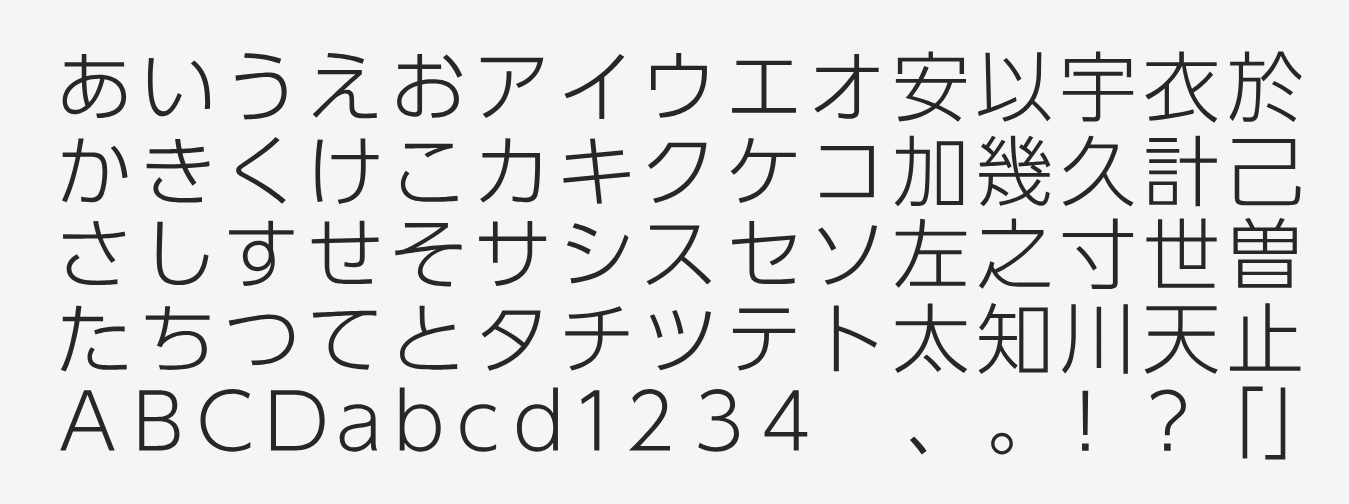
クラウド請求書作成サービスで
UD新ゴを採用
インボイス制度で利用者が広がる
電子帳票をよりアクセシブルに
インボイス制度の導入や電子帳簿保存法の改正に伴って請求書の電子化が進み、請求書発行サービス市場の拡大が続いている。ユーザーの選択肢も増えるなか、中小企業や個人事業主にフィットしたサービスで存在感を示しているのが、ヴェルク株式会社の開発したクラウド請求書作成サービス『board』だ。
同社は業務効率化につながる機能の開発はもちろん、Webアクセシビリティの改善にも積極的に取り組んでいる。より多くの人にとって見やすい帳票とするべく、2023年10月には書類で使用するフォントを変更し、新たにモリサワのユニバーサルデザインフォント(以下、UDフォント)である「UD新ゴ」を導入。同社の代表取締役であり『board』開発者である田向祐介氏に、フォント導入の経緯やアクセシビリティへの取り組みなどを伺った。
中小企業のビジネスモデルに即した『board』の設計
『board』は見積書や請求書の作成をはじめ、営業管理や受発注管理などの周辺業務を一元的に管理できるクラウドサービスで、数人から数十人規模の中小企業や個人事業主を主な対象としている。開発の経緯をたずねると、「僕が欲しかったんです」という答えが返ってきた。
「開発当時(2014年)、請求書を作成するサービスはあっても、業務管理ができる中小企業向けのサービスが無かったのです。業務管理までできるサービス自体は存在しましたが、支払う利用料のケタが違い、中小企業にとっては現実的ではなかった。それならば自分で作ろう、事業にならなかったら社内システムにすればいいや、という感覚でスタートしました」
『board』の開発には、実際に経営と実務を兼務する田向氏の「ユーザー目線」がふんだんに盛り込まれている。例えば、「案件ごとの管理」はそのひとつだ。一般的な請求書発行サービスの単位は「帳票」であり、単独で請求書を作成することもできるが、『board』は案件という一つの箱を作成した上で、そこにひもづく見積書や請求書などを入れて管理する。
「同時にいくつもの仕事を抱える事業者にとって“案件”はごく当たり前の概念ですが、それを軸にしたサービスは存在せず、自分自身が非常に困っていたんです。案件ごとで業務を管理する方法は、当社のような受注業務をメインで行っている会社には非常に良くフィットする。『board』が評価されている大きな理由だと思います」。
また、「従業員数10人程度の会社がバックオフィスのシステムに月数万円は払えないので、抑えた価格設定にした」と田向氏が言うとおり、法人向けプランでも月額数千円という圧倒的なコストパフォーマンスで提供。その他さまざまな外部サービスと連携して使える点など、現場の業務に即したサービス設計が多くのユーザーに評価されている。
“board利用者の先にいる人たち”にも届けるために「UD新ゴ」を導入
『board』はCUD(カラーユニバーサルデザイン)認証を取得しており、2019年5月以降、ログイン内の画面をCUD対応としている。認証取得のきっかけは、「日本人男性の5%」を占めるという色弱者の割合だと田向氏は話す。
「実は5%って、開発当時のboard利用者における、Webブラウザ『Safari』のシェア率よりも高かったんですよ。エンジニアとしてクロスブラウザ対応※1と同様に、多様な色覚への対応も必要ではないかと考えていたところ、偶然にもユーザーの方からCUDO(カラーユニバーサルデザイン機構)を紹介していただく機会があり、取り組むことになりました」
※1クロスブラウザ対応: Webブラウザの種類を問わず、Webサイトの見え方・動作を統一させること
『board』の案件一覧画面は受注ステータスがひと目でわかるよう、赤・緑・黄などに色分けされているが、色覚タイプによっては赤と緑の区別がつかない。また、注意喚起に使用する赤字も、赤と黒の識別ができない色覚タイプの人にとっては意味をなさない。より多くの人に伝わるようにするには配色を変更する必要があるが、大きな改変は既存ユーザーが混乱するおそれがある。そこで、既存の色の系統を維持しながらCUD対応の配色に調整しなければならず、この作業が非常に大変だったという。ただこの経験が「アクセシビリティ(より多様な利用者が製品やサービスを利用できること)」への知見を深める契機となった。
「ディスレクシア※2のように、私たちが考える“見えやすさ”とは別の理由で文字を識別しづらい方がいることも学びました。僕は長年読みやすいフォントを選んできたつもりでしたが、完全に主観でしかなかったことに気づかされたのです。本当に読みやすいフォントとは、きちんと研究された上で設計されているのだと、文字に対する概念が変わりました」
※2ディスレクシア:文字の読み書きに限定した困難がある学習障害
今回、書類PDFで使用するフォントにUD新ゴを導入した理由も、アクセシビリティ改善の一環であるという。
「『board』で作成した見積書や請求書を受領する側、つまり“board利用者の先にいる人”がどのような人なのか、こちらがうかがい知ることはできません。ならば、私たちのサービスで作成する書類にも読みやすい文字として設計された文字を使うべきだと思いました。フォントの知識が全くなかったので、モリサワさんにはアクセシビリティについても伝えた上で、フォント候補をピックアップしてもらいました」
バックオフィスのシステムは一画面の中に集約する情報が多いため、見やすさと情報量を両立させるバランスが難しい。特に見積書や請求書のように多くの数字が並ぶ帳票に関しては、文字幅が広いフォントだと認識しづらくなってしまう。複数のフォントで実際に検証を繰り返し、もっともバランスがよいと感じた「UD新ゴ」の採用を決めた。ただ、検証フォントの組み込み時には思わぬアクシデントもあったという。
「UD新ゴの検証フォントを『board』へ組み込んだ際は一度レイアウトが崩れてしまったのですが、そこをモリサワさんに細かくフォローしていただきました。フォントは“完成した製品を買う”というイメージだったので、正直なところこれほど丁寧に対応してもらえるとは思っておらず、とてもありがたかったです」と田向氏は振り返る。
アクセシビリティはUDフォントを使うだけでも改善できる
UDフォントの導入は、思いのほか反響があったという。
「ユーザーからは『とても見やすくなった』や『UD新ゴが使えるの!?』といった声が届きました。そもそも、バックオフィスのサービスには有償フォントが使えるイメージがなかったためか、かなり反響がありましたね。書類を受領する方を想定した対応だった点にも、共感や評価の声が集まりました。面白いなと感じたのは、デザイナ―など普段フォントに対して関心が高いであろう人たち以外からの反応も多かったこと。それだけ、UDフォントの認識が高まってきているということなのかもしれません」
インボイス制度施行を機にクラウドサービスの利用が広がり、同社への問い合わせも増えているという。UDフォントの導入とインボイスとの直接的な関連はないが、サービスの利用人口自体が増えれば電子帳票を目にする人も当然増える。
「アクセシビリティの改善は個人の知識に依存していてはなかなか広まりません。日々の業務で使用している仕組みの中でUDフォントを利用することで、board利用者の先にいる人たちにも届けられ、リーチできる層が広がる。そういう意味では、このタイミングで導入してよかったと思っています」
CUDの検証のほか、スクリーンリーダー(コンピュータの画面読み上げソフト)を利用した操作への対応など、現在も継続的に取り組みを進めている。アクセシビリティ改善はハードルが高いように思えるが、「UDフォントは非常に取り組みやすい改善方法のひとつ」と田向氏は話す。
「CUDやスクリーンリーダーは地道な検証作業や技術的な問題をクリアする必要がありますが、UDフォントは導入するだけで確実に文字を読みやすくなる人がいる。もちろんそれだけですべてが解決するわけではないですが、着実に改善すると思うのです。たとえば日常業務で作成する資料などでもUDフォントを使うことが当たり前になるように、フォントや文字の見やすさを研究し続けているモリサワさんが今後も情報発信をしてくれることを期待しています」
ユーザーからの高い支持を得て、『board』の有料導入社数は5,000社を突破(2024年1月時点)。今後はどのような展開を考えているのか聞いた。
「当社は“10人規模の会社で1万社が使うサービスを”というスタンスで経営しています。少人数のまま、なるべく人に依存せず事業展開していきたいですね。当社の規模でアクセシビリティ対応を行っていることによく驚かれるのですが、確かに短期的な事業拡大を優先するやり方ではないかもしれません。ですが、今回のUDフォントの導入も含め、お客様やその先にいる人に届けるサービスのクオリティーは上げていきたいし、そういった改善をずっと続けていきたいという強い想いがあります。なので経営者としては、今後もよいシステムを開発できる事業体力を維持しつつ、なおかつ自分も創り手として質の良いサービスを提供していきたいと考えています」
「より多様な利用者が快適に利用できる」環境を当たり前にするために、ヴェルクの挑戦はまだまだ続く。その挑戦が一歩ずつ、けれども確実に、世の中を変えていくはずだ。